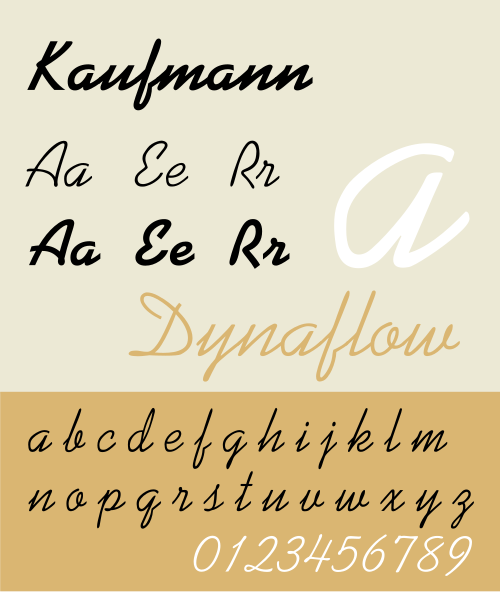
| カテゴリ | カジュアルなスクリプト |
| デザイナー | マックス・R・カウフマン |
| 鋳造所 | アメリカンタイプファウンダーズ |
| 再発行ファウンドリ | Bitstream、Elsner+Flake、Linotype、Adobe Type、Scangraphic、Tilde、SIA、URW |
Kaufmann は、 1936 年に Max R. Kaufmann がAmerican Type Founders (ATF) のために作成したブラシ スクリプト書体の名前です。線の太さは単色です。大文字は自由に描画されますが、小文字は高さと幅がより規則的で、筆記体の手書きを思い起こさせます。小文字はぴったりとフィットし、接続スクリプトの外観に影響を与えます。dはループ状になっています。
大文字と小文字の両方の流動的な形状と均一な太さのストロークの組み合わせにより、カウフマンはネオンサインの製作で人気を博しました。
使用法
2001年以降、この書体の若干変更された形式が、ポップアイドルシリーズやさまざまな国際的スピンオフのロゴに使用されています。最も顕著な変更点は、アメリカンアイドル、オーストラリアンアイドル、アジアンアイドルのロゴの大文字「A」に、長く様式化されたフリックが追加されたことです。ニュージーランドアイドルのロゴに使用されている「Z」も、標準的なカウフマンの「Z」とは大きく異なります。
カウフマンは、1970年から1994年にかけてのトップス社の野球カードに選手名を表示するためにも使用され、ニューヨーク市のエド・サリバン劇場の看板やデイヴィッド・レターマンのレイト・ショーのロゴにも登場した。
この書体の小文字のrのバージョンは、デイビッド・J・グリフィスによる学部生向けの電気力学の本で使用されています。これは、ソースポイントからフィールドポイントまでの距離を示すために使用され、他のテキストでは通常、このように表記されます。 [1] [2]